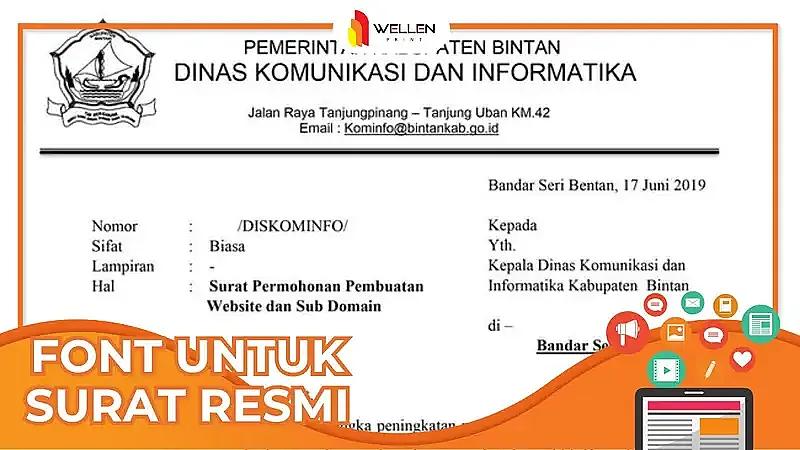
10 Rekomendasi Font untuk Surat Resmi, Tampil Lebih Kredibel!
Aktivitas korespondensi melalui surat resmi merupakan salah satu media komunikasi profesional di berbagai aspek, baik pekerjaan, pemerintahan, maupun akademik. Setiap elemen surat harus diperhatikan dengan cermat karena membawa pesan penting sekaligus menjadi representasi pengirim. Salah satu elemen yang tidak kalah penting adalah font untuk surat resmi itu sendiri.
Pemilihan font sering kali asal-asalan, padahal dari ribuan opsi, tidak semuanya cocok untuk penulisan surat resmi. Ada font yang memiliki karakteristik tegas dan rapi, sehingga cocok untuk kebutuhan korespondensi profesional. Namun, ada pula yang dibuat khusus untuk kebutuhan kasual. Berikut daftar 10 font untuk membuat surat resmi yang paling direkomendasikan.
ToggleTimes New Roman menduduki posisi pertama rekomendasi font untuk surat resmi. Awal mula kehadirannya di tahun 1931 oleh Stanley Morison dan Victor Lardent untuk kebutuhan penulisan surat kabar Inggris The Times mengukuhkan pengaplikasiannya yang memang diperuntukkan sektor profesional. Font ini didesain untuk keterbacaan maksimal dengan ketebalan garis jelas dan tegas.
Seiring waktu, Times New Roman semakin banyak digunakan dalam berbagai kebutuhan pengetikan dokumen, bahkan ditetapkan sebagai pengaturan default. Menjadikannya sebagai font huruf untuk surat resmi merupakan pilihan aman yang menunjukkan profesionalitas tinggi Anda.
Selain Times New Roman, Arial juga salah satu font populer yang menjadi standar dokumen resmi, termasuk surat. Bagian dari sans-serif yang didesain Robin Nicholas dan Patricia Saunders tahun 1982 ini merupakan versi adaptasi modern dari Helvetica yang lebih tua. Karakteristik hurufnya bersih, rapi, dan minimalis tanpa kait di bagian ujungnya.
Tingkat keterbacaan Arial sebagai font style untuk surat resmi sangat bagus, baik untuk tampilan digital maupun hasil cetak. Menggunakannya sebagai font untuk pengiriman surat resmi dapat menciptakan kesan ramah dan bersahabat kepada penerima surat, tanpa menanggalkan batas profesional.
Calibri merupakan bagian font sans-serif humanist yang tidak kalah familiar dari dua font sebelumnya. Bahkan, di versi Microsoft Office 2010 ke atas, Calibri menjadi font default menggantikan Times New Roman dan Arial. Calibri memang didesain Lucas de Groot sebagai bagian seri font ClearType Microsoft untuk mengoptimalkan tingkat keterbacaan di layar.
Ciri khas Calibri adalah memiliki sudut yang sedikit membulat, membuat proporsinya lebih seimbang dan jarak antar huruf lebih baik sehingga kenyamanan baca meningkat, bahkan untuk teks panjang. Penerima surat akan merasakan keramahan dari penggunaan font Calibri, tapi tetap dalam batasan profesional.
Cambria yang juga sering digunakan sebagai font untuk spanduk dirilis bersama dengan Calibri, dari desainer berbeda, yaitu Jelle Bosma. Seri ClearType Microsoft ini menjadi alternatif font Calibri untuk mengoptimalkan keterbacaan di layar. Cambria memiliki goresan modern yang kuat dengan spasi cukup luas. Cocok untuk surat dengan banyak angka di dalamnya.
Georgia merupakan pasangan font Verdana yang dirilis tahun 1993 oleh desainer tipografi Matthew Carter. Tinggi huruf Georgia lebih besar dari font serif pendahulunya, sehingga memiliki tingkat keterbacaan yang superior, baik untuk tampilan digital maupun media cetak. Karakternya unik karena menambahkan nuansa kaligrafi yang halus, jadi tampak elegan.
Menjadikan Georgia sebagai font untuk surat resmi merupakan alternatif tepat untuk Times New Roman yang kadang dirasa terlalu old school. Meskipun demikian, citra profesional tetap tampak jelas dari Georgia, hanya saja terasa lebih bersahabat bagi penerima surat tersebut.
Font untuk surat resmi apa yang bisa menjadi pilihan berikutnya adalah Garamond. Hadir sejak abad ke-16, saat ini font serif yang kental dengan gaya lama ini memiliki banyak variasi, seperti: Adobe Garamond, EB Garamond, atau Monotype Garamond. Meskipun begitu, karakteristik utamanya sebagai huruf organik dengan efisiensi ruang terbaik tetap terjaga.
Menggunakan Garamond sebagai font untuk surat resmi akan memaksimalkan informasi yang dapat dimuat tanpa perlu khawatir akan tingkat keterbacaannya. Garamond sejak dulu lekat dengan penggunaan untuk kebutuhan profesional tapi tidak terlalu kaku.
Anda tidak perlu download font untuk surat resmi karena memiliki Helvetica sebagai salah satu font default di Microsoft Office. Rancangan Max Miedinger dan Eduard Hoffmann tahun 1957 ini menjadi salah satu koleksi sans-serif terpopuler. Ketegasan dan kesederhanaan goresan huruf menciptakan citra profesional yang kuat jika Anda menggunakannya untuk aktivitas korespondensi.
Book Antiqua juga font untuk surat resmi yang sangat direkomendasikan. Font serif ini didesain berdasarkan kaligrafi Renaisans Italia. Ciri khasnya memiliki kontras tebal yang adil dan tinggi yang cukup, sehingga tingkat keterbacaannya sangat baik. Font dengan sentuhan klasik tradisional yang kuat ini akan menciptakan citra elegan dan profesional yang kuat.